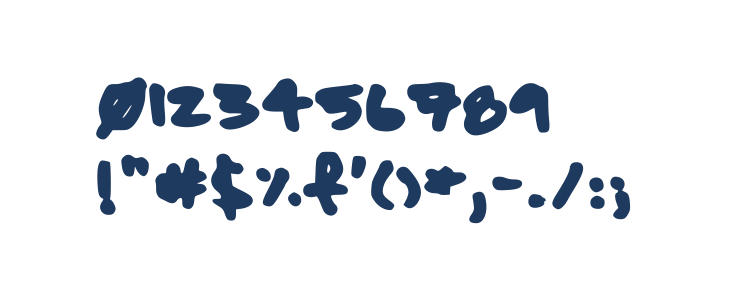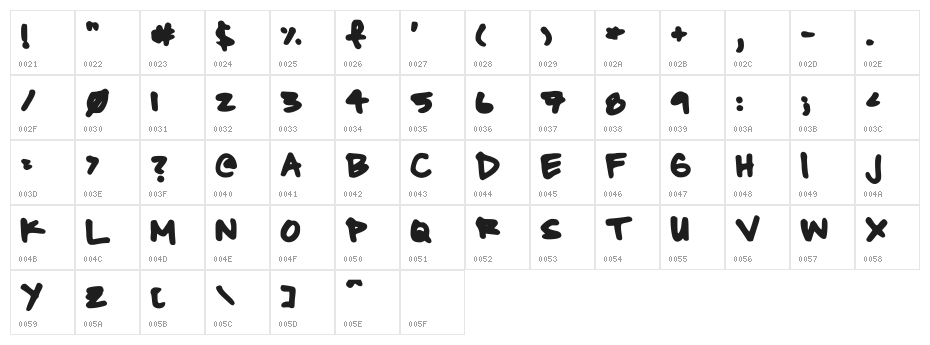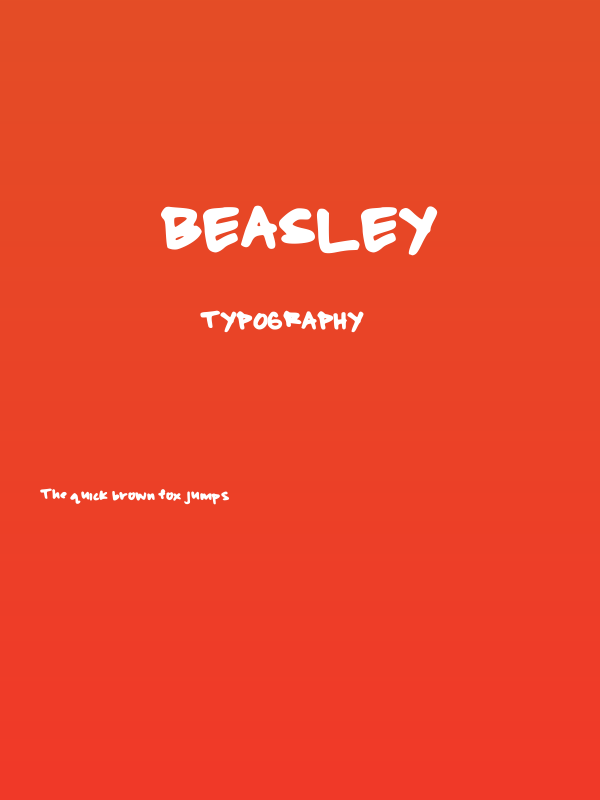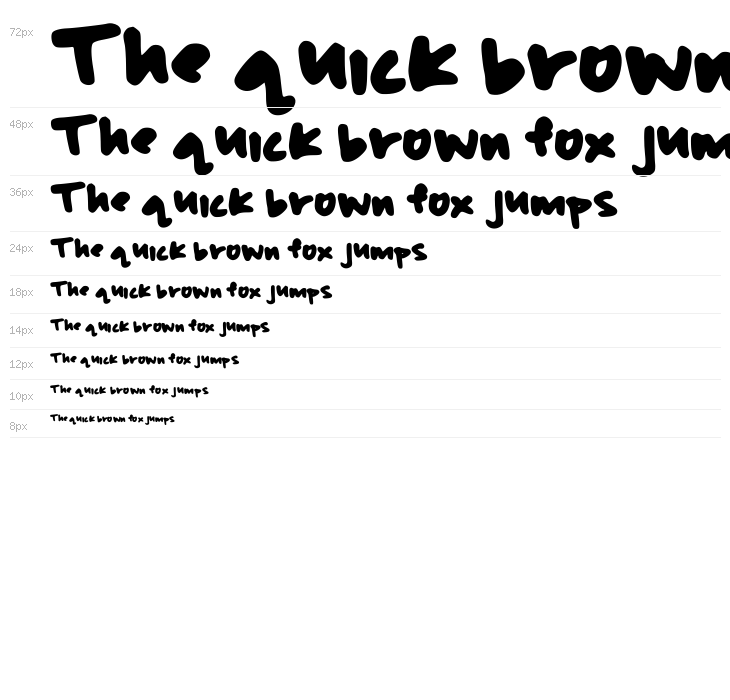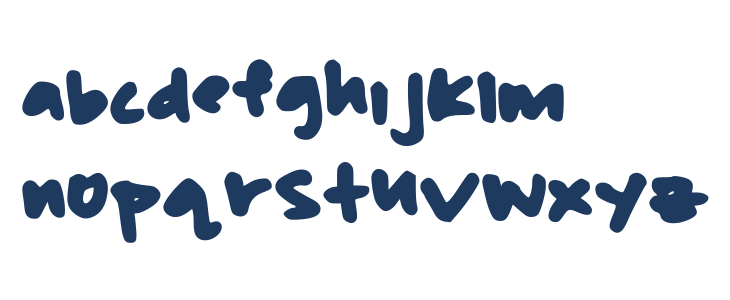
beasley Font
| Stile generale | Playful, Casual |
| Caso d'uso | Headlines, Logos, Informal Text |
| Progetti proposti | Ideal for children's books, playful branding, greeting cards, and casual invitations. |